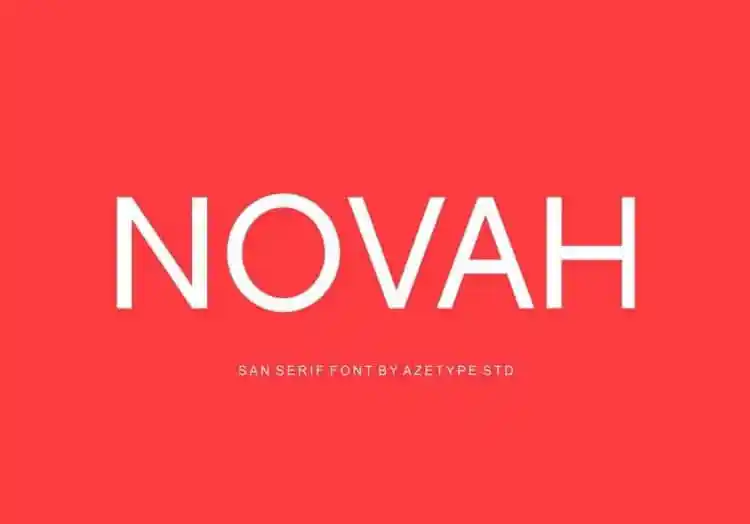
Novah Sans Free Font – Download Grátis
Novah Sans é uma fonte sans-serif que combina maravilhosamente com letras escritas a mão. Seu estilo limpo e moderno faz dela uma escolha ótima tanto para projetos individuais quanto para conjuntos mais elaborados, proporcionando um equilíbrio elegante e profissional. A sua versatilidade é impressionante: pode ser usada em logotipos e marcas, cartões de visita e apresentações, headlines e letras personalizadas, posters, identidades corporativas, mensagens de texto, títulos em revistas, cabeçalhos em sites, layouts para dispositivos móveis, artigos de quotes e publicidade. É perfeita para qualquer projeto criativo que exija uma harmonia sofisticada entre formas clássicas e letras modernas. Novah é a fonte certa quando você precisa de uma solução sólida e versátil para seus projetos visuais, mantendo um equilíbrio elegante e profissional.